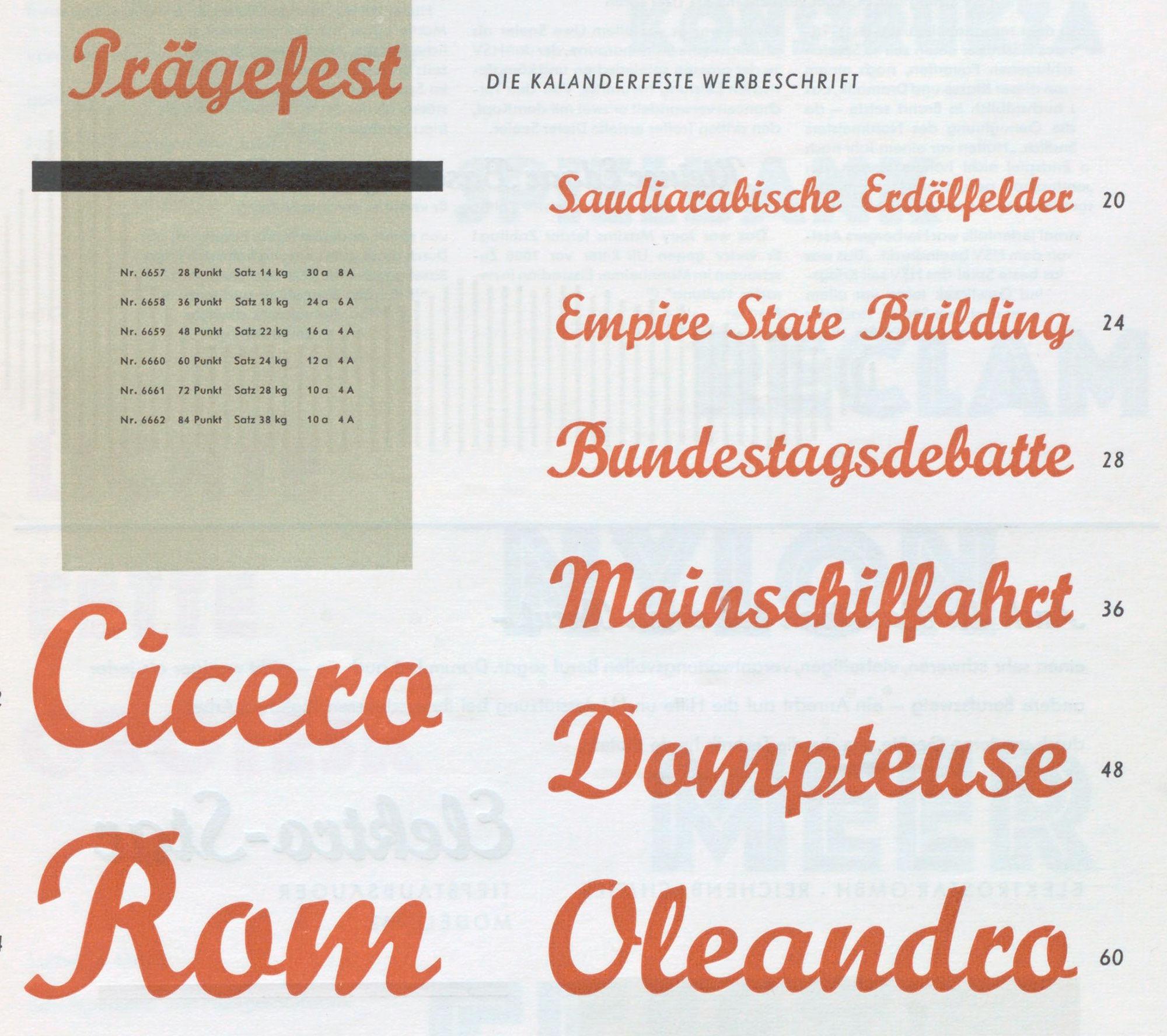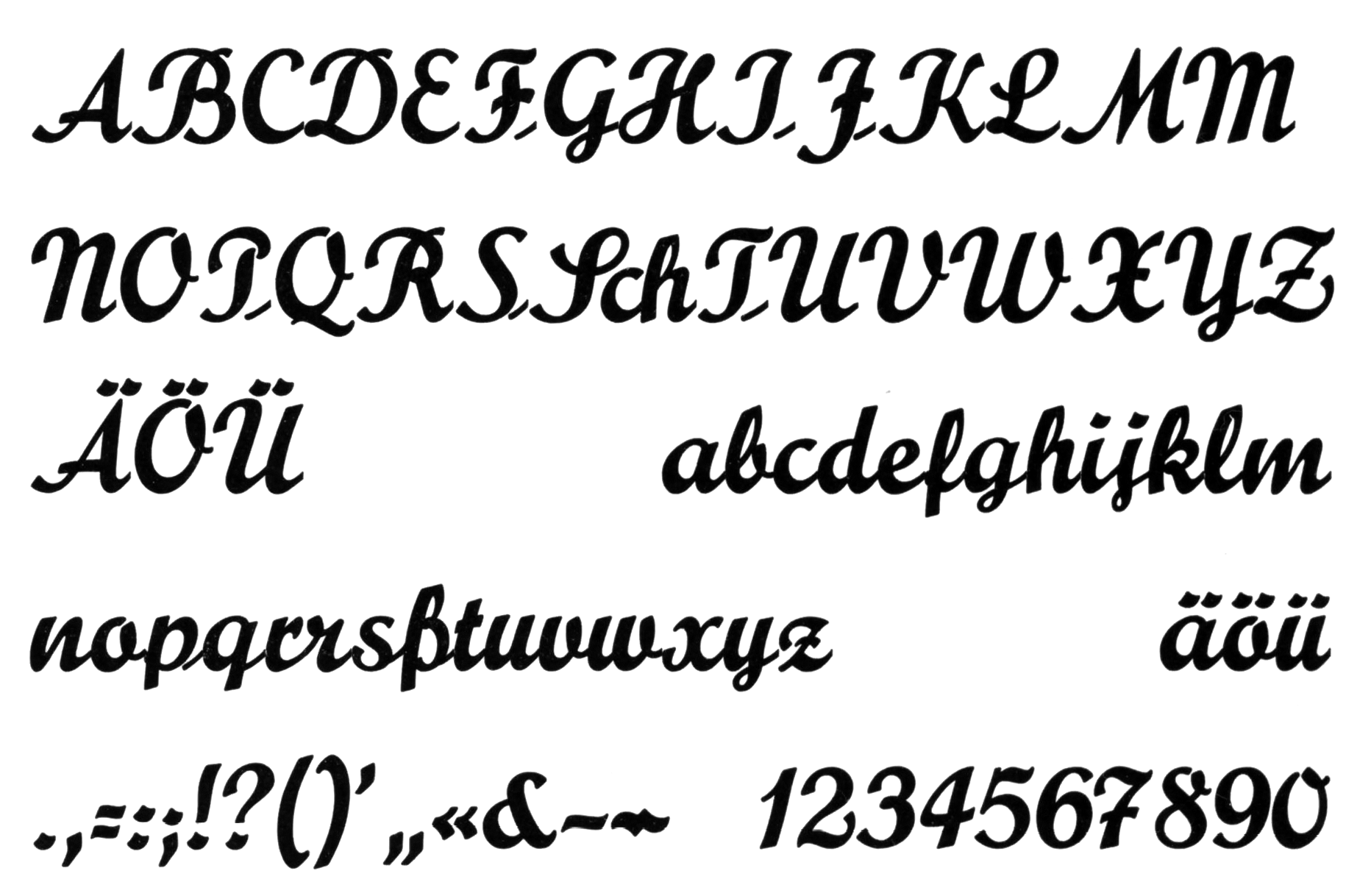
Font-Wiki: Prägefest
Die Prägefest ist eine verbundene Schreibschrift von Paul Eduard Lautenbach und erschien 1926 über Ludwig & Mayer. Der Name verweist darauf, dass die Schrift auf geradem Kegel ohne überhängende Elemente gegossen wurde.
Eine kostenlose Digitalisierung gibt es von Peter Wiegel.